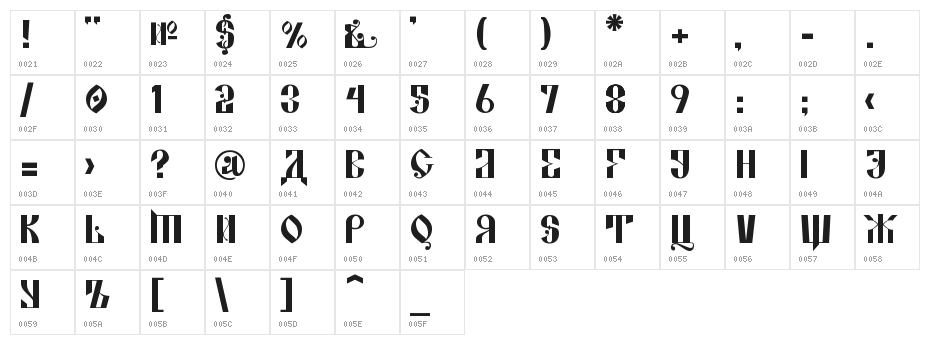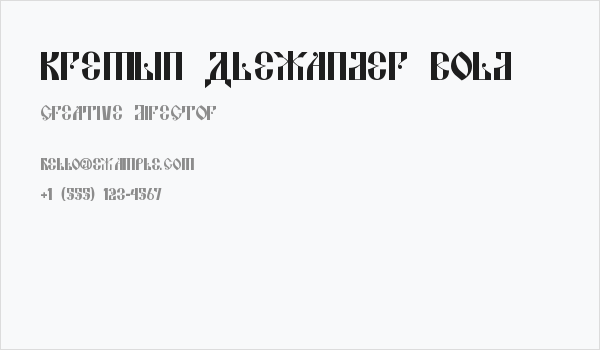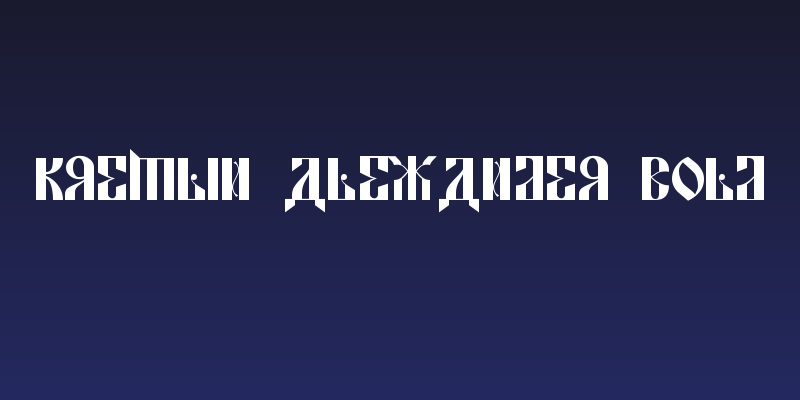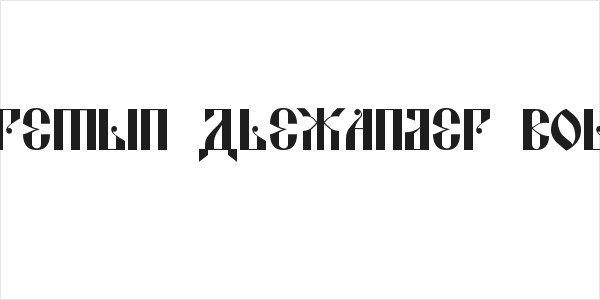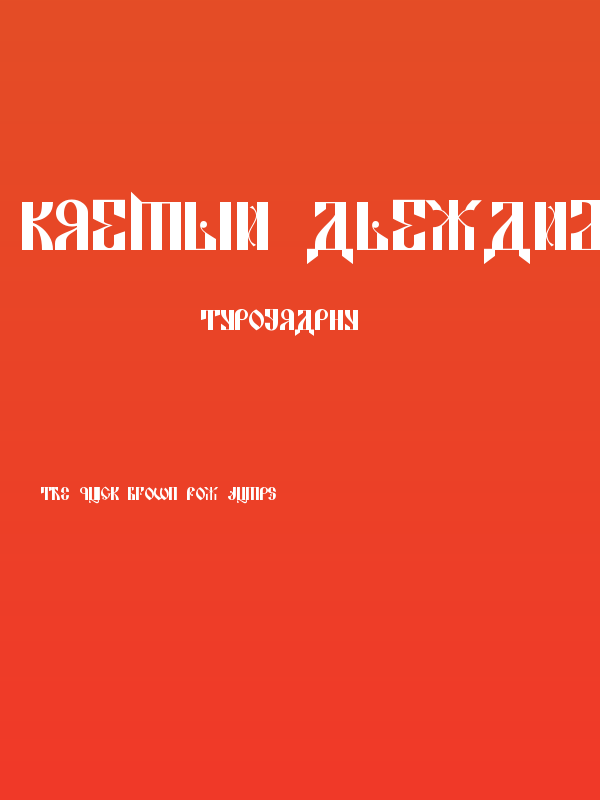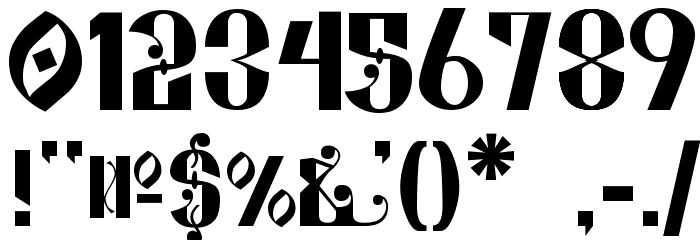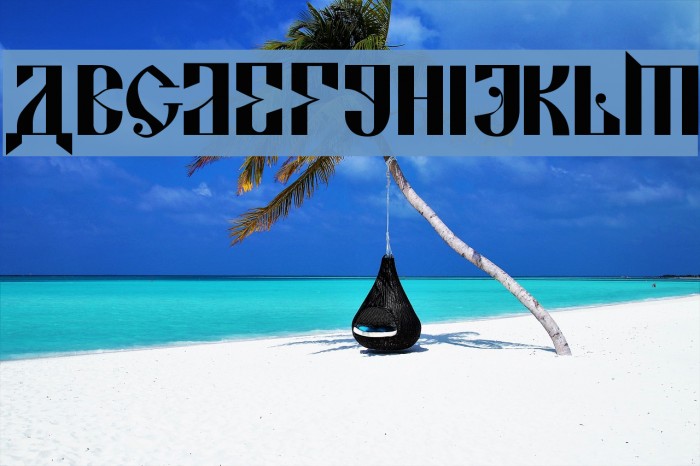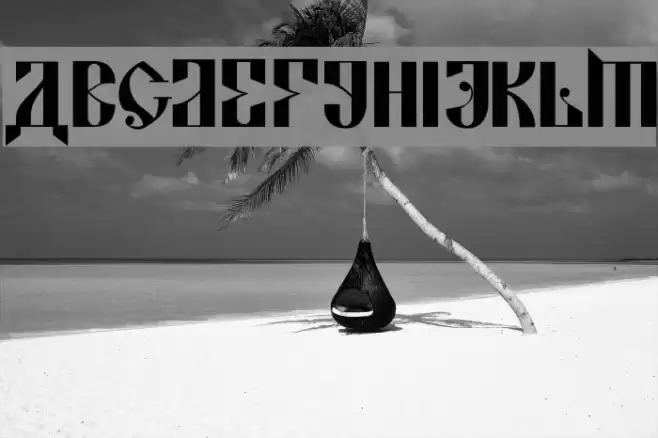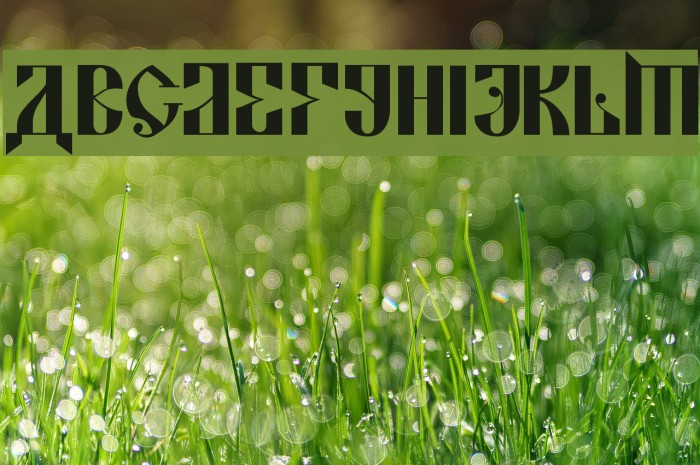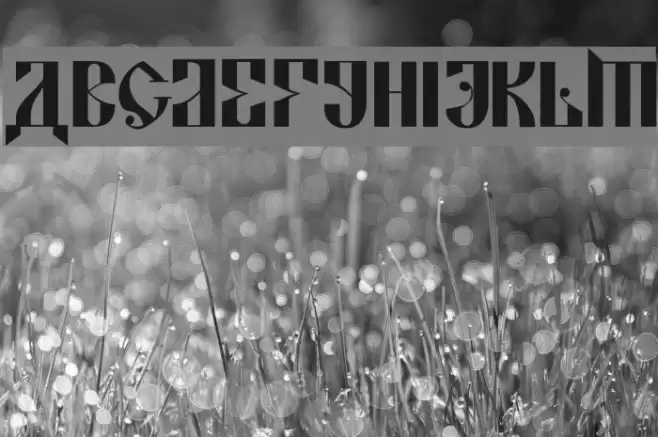
Kremlin Alexander Bold Font
| Projetos propostos | Ideal for cultural event posters, historical themed designs, book covers, and branding that requires a touch of elegance and tradition. |